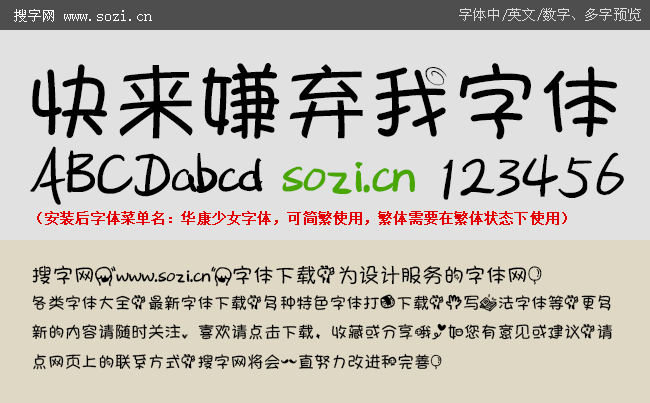
快來嫌棄我字體
搜字網(wǎng)給大家提供一款很卡通的手機(jī)中文字體下載。修改者將它命名為快來嫌棄我字體,這款手機(jī)字體是以華康少女體為原形,字體的個別筆畫和標(biāo)點被改成了非常有趣的卡通圖案,華康少女字體電腦版是一款可愛俏皮的電腦字體。字型中充滿年青人蓬勃的氣息與自由奔放的性格,字體比較圓滑,特別適合喜歡手機(jī)字體個性一些的朋友在手機(jī)上安裝使用。